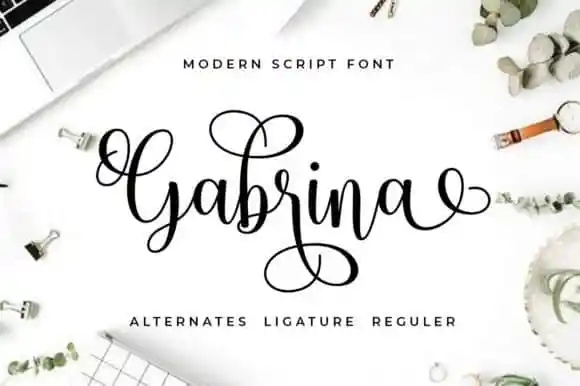
Gabrina Calligraphy Font – Download Grátis
Gabrina Calligraphy Font é uma elegante tipografia script que traz muitas alternativas de caracteres para qualquer projeto de design. Inspirada no estilo clássico da tipografia, ela carrega seu próprio charme único. Esta fonte é perfeitamente adequada para se tornar o destaque em headlines, seja grande ou pequeno, bem como para blocos de texto que apresentam tanto variações extremas quanto variáveis sutis. Seja aplicada para sites, impressões, animações ou qualquer outro uso – a fonte Gabrina vai brilhar e trazer um toque único ao seu trabalho. Ideal para designers em busca de uma paleta de opções versáteis que sejam tanto elegantes quanto atemporais, Gabrielina é perfeita para incorporar em suas criações.